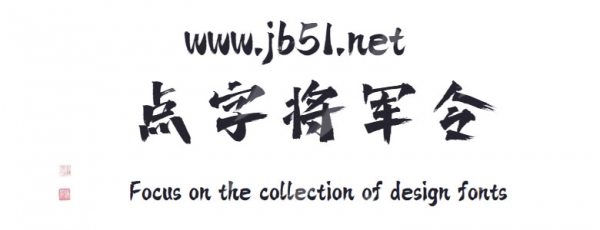
點字將軍令是由點字庫推出的藝術(shù)字體,字體提筆鸞翱鳳翥,最后一筆用破筆飛白表現(xiàn)飛流直下之勢,適合應(yīng)用于藝術(shù)設(shè)計、各類廣告和產(chǎn)品包裝設(shè)計等領(lǐng)域。
提筆鸞翱鳳翥,最后一筆用破筆飛白表現(xiàn)飛流直下之勢。少牽絲連帶,多方折表現(xiàn)出果斷決絕的立意。